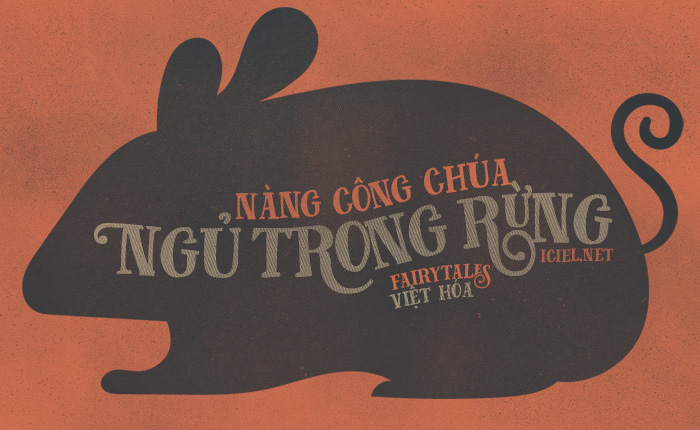
Khám phá sức mạnh của Font việt hoá iciel Fairy Tales trong thiết kế hiện đại
Trong thế giới đồ họa đầy màu sắc, việc tìm kiếm một mẫu Font Chữ phù hợp để truyền tải cảm xúc là điều vô cùng quan trọng. Font việt hoá iciel Fairy Tales nổi lên như một lựa chọn hoàn hảo cho những ai yêu thích vẻ đẹp cổ điển và bay bổng. Được thiết kế dựa trên cảm hứng từ những trang sách truyện cổ tích phương Tây, bộ phông chữ này mang đến sự kết hợp tinh tế giữa nét chữ viết tay uyển chuyển và sự chắc chắn của các ký tự hiện đại. Đối với các bạn học sinh và giáo viên, đây là công cụ đắc lực để biến các bài thuyết trình hay tài liệu học tập trở nên sinh động và thu hút ánh nhìn hơn bao giờ hết.
Ưu điểm nổi bật của Font việt hoá iciel Fairy Tales
Thiết kế đậm chất nghệ thuật
Font việt hoá iciel Fairy Tales sở hữu những đường nét uốn lượn đặc trưng, tạo nên cảm giác huyền ảo và lãng mạn. Mỗi ký tự đều được chăm chút kỹ lưỡng để đảm bảo tính thẩm mỹ cao nhất, giúp các tiêu đề sách, thiệp mời hay poster quảng cáo trở nên nổi bật. Sự mềm mại trong cấu trúc chữ giúp người xem cảm thấy dễ chịu và dễ dàng liên tưởng đến những câu chuyện thần tiên kỳ bí.
Khả năng hiển thị tiếng Việt hoàn hảo
Một trong những lý do khiến bộ phông này được yêu thích tại Việt Nam là nhờ quá trình Việt hóa tỉ mỉ. Các dấu thanh được đặt vị trí chuẩn xác, không bị lỗi hiển thị hay mất nét khi gõ văn bản dài. Điều này cực kỳ hữu ích cho các dự án thiết kế nội dung giáo dục hoặc trang trí báo tường tại trường học.
Cách ứng dụng Font việt hoá iciel Fairy Tales hiệu quả
Để tận dụng tối đa vẻ đẹp của bộ chữ này, bạn nên kết hợp chúng với các tông màu pastel nhẹ nhàng hoặc màu vàng đồng sang trọng. Phông chữ này phát huy tác dụng tốt nhất khi làm tiêu đề chính hoặc các đoạn trích dẫn ngắn cần sự nhấn mạnh. Việc sử dụng Font việt hoá iciel Fairy Tales không chỉ nâng tầm giá trị thẩm mỹ mà còn giúp thông điệp của bạn chạm đến trái tim người xem một cách tự nhiên nhất. Nếu bạn đang tìm kiếm giải pháp làm mới diện mạo cho các thiết kế của mình, hãy trải nghiệm ngay Font Miễn Phí, Font Việt Hóa, Font việt hoá iciel Fairy Tales để cảm nhận sự khác biệt rõ rệt trong từng tác phẩm nghệ thuật.